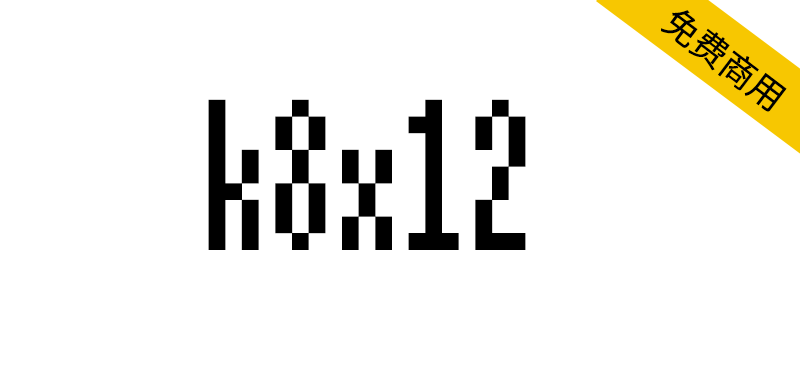
k8x12 是一种 8×12 点的日语像素字体。它支持JIS级别1和级别2,并包含一些其他符号。
k8x12 有变体,称为 k8x12L 和 k8x12S,它们改变了 Kanji 以外的字形。
k8x12 は 8×12 ドットの日本語ビットマップフォントです。
JIS 第一・第二水準をサポートしており、その他の記号も一部含んでいます。
k8x12 には、漢字以外の字形を変更した
k8x12L, k8x12S というバリエーションが存在します。
K8x12,原来的。k8x12,オリジナル。
k8x12L,垂直长假名的变体。k8x12L,仮名を縦に長い形にしたバリエーション。
k8x12S,非汉字的变体,高度为 8 个点。浊音标记和半浊音标记在其上。我们知道以 8 x 8 点为单位处理图形的旧游戏机的限制。
k8x12S,非漢字を高さ 8 ドットにしたバリエーション。濁点、半濁点はその上に乗る形です。
8×8 ドット単位でグラフィックを扱うような、昔のゲーム機等の制限を意識しています。